Canvaで数字をおしゃれに見せるフォントガイド|用途別におすすめを厳選
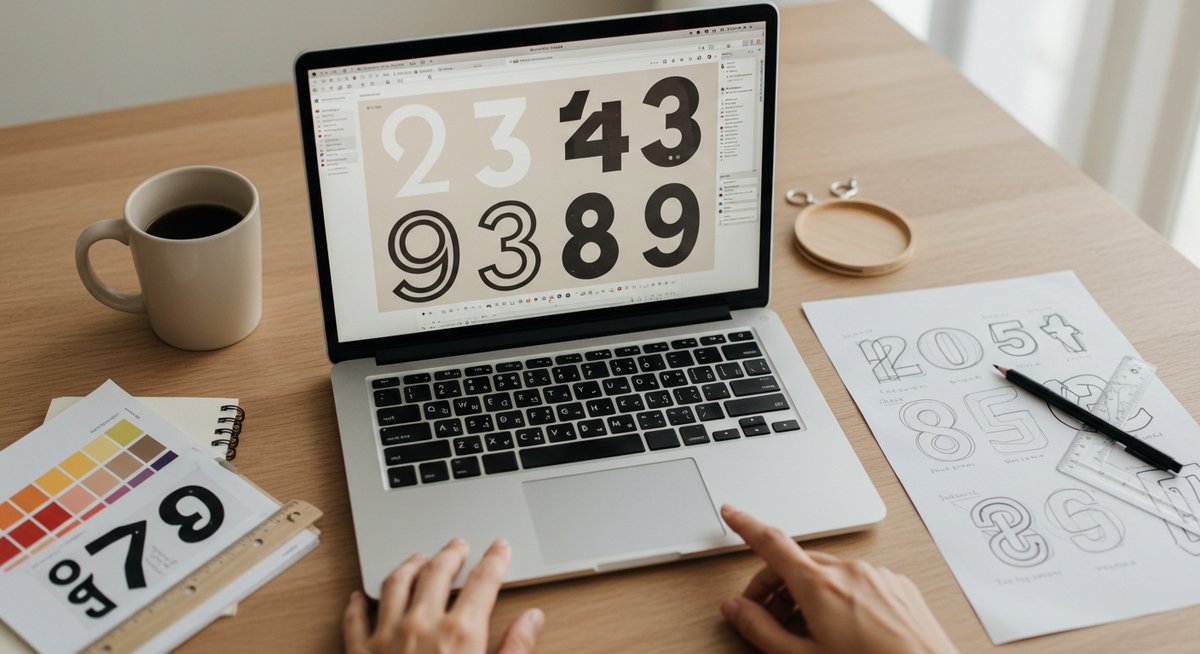
デザインで数字の見え方が変わると、伝わり方がぐっと良くなります。ここではCanvaで使う数字フォントに絞って、おすすめフォントや選び方、使い方のコツをわかりやすくまとめました。読みながら自分のプロジェクトに合うフォントが見つかるように書いていますので、気軽に試してみてください。
Canvaで使う数字のフォントのおすすめはこれ
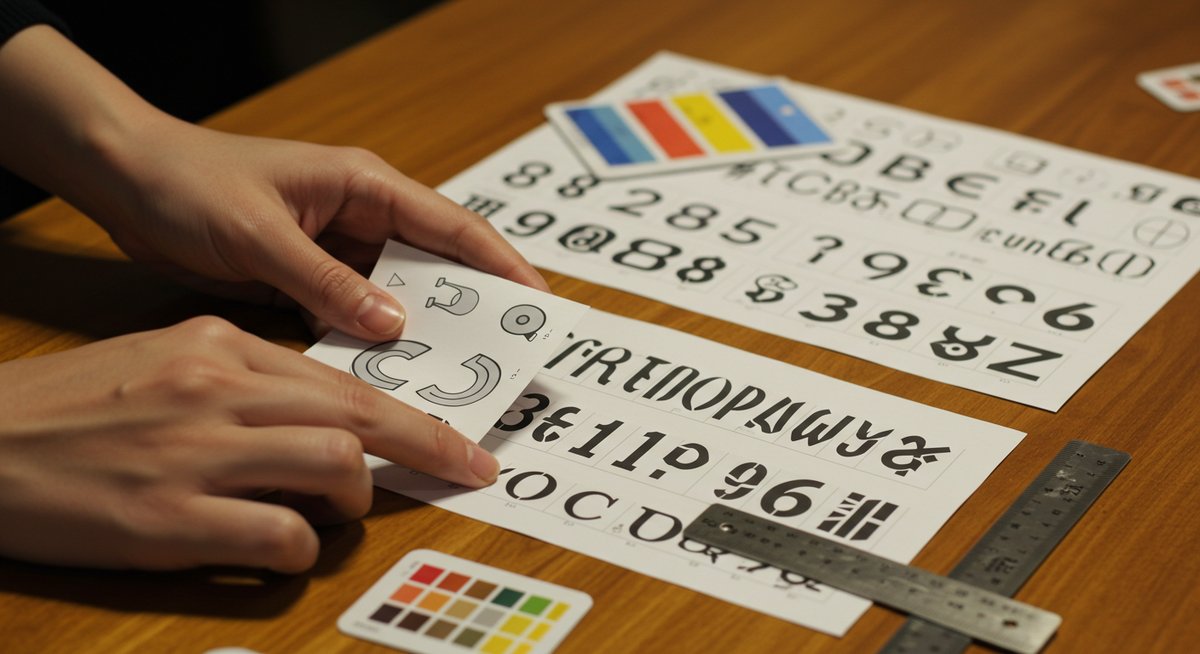
ここではタイトルや見出し、グラフ、金額表示、手書き風まで用途別に向くフォントを紹介します。各フォントの特徴と、どんな場面で使うと効果的かをシンプルにまとめました。実際にCanvaで試すときの参考にしてください。
見出し向けのおしゃれな欧文フォント Lovelace Road Race
Lovelace Road Raceは華やかで個性のある欧文フォントです。数字のラインが細く伸びる部分と太い部分のコントラストがあり、見出しやバナーで目を引く効果があります。特にイベント告知やファッション系のデザインで映えます。
数字は装飾性が高いため、大きめサイズで使うのが向いています。小さく表示すると細部がつぶれやすいので注意してください。スペースに余裕がある見出しや、ビジュアル重視のサムネイルに合わせるとバランスが良くなります。
使う際は文字間を少し詰めたり、影をつけて立体感を出すとさらにおしゃれに見えます。背景はシンプルな単色や淡いグラデーションにすることで数字が浮き立ちます。
グラフや表で読みやすいゴシック系 DIN Next Noto Sans
DIN NextやNoto Sansは直線的で安定感のあるゴシック系フォントです。数字の輪郭がはっきりしているため、グラフや表、インフォグラフィックでの読みやすさに優れます。視認性を重視する場面で安心して使えます。
桁が多くなる数値や小さなフォントサイズでも判読しやすく、資料やレポート、プレゼン資料との相性が良いです。等幅に近いプロポーションのフォントを選ぶと、表組みで桁が揃いやすく見栄えが整います。
配色はコントラストを意識するとさらに読みやすくなります。背景が濃い色なら白や淡い色の数字を、淡い背景ならダークな色を使うと視認性が上がります。
金額や日付表示に向く安定したフォント Oswald Futura
OswaldやFuturaは角が整っていて、金額や日付の表示に向く落ち着いたフォントです。視線を奪わずに情報を伝えられるため、ECサイトの価格表示やイベントの日程案内などで使いやすい特徴があります。
桁が連なる場面でも見やすく、太さのバリエーションがあれば強調したい部分だけ太字にすると読みやすくなります。数字のみ太くするなどアクセントをつけると重要な情報を強調できます。
画面や紙面での馴染みも良いので、ブランドの本文フォントに近い系統を選ぶと統一感が出ます。余白を適度に取って読みやすさをキープしましょう。
手書き風で親しみが出るフォント Allura Dancing Script
AlluraやDancing Scriptは手書き感のあるフォントで、カジュアルさや親しみを出したい時に向いています。日付や小さな数値をアクセントとして使うと、堅すぎない印象になります。
ただし装飾が強いので長い数列や重要な数値の表示には向きません。短めの数字や見出しの一部で使うとデザインに温かみが加わります。
文字サイズを大きめにして読みやすさを確保し、背景にはシンプルな色を使うと文字が浮かび上がります。合うフォントと組み合わせて使うことでバランスよく見せられます。
日本語デザインに合わせやすい無料フォント Noto Sans JP 筑紫Aオールド明朝
Noto Sans JPはクセが少なく読みやすい日本語ゴシックで、数字との相性も良いです。筑紫Aオールド明朝はセリフで品のある印象を与えます。和文デザインの中でも数字の雰囲気を変えたい時に便利です。
和文が主体のデザインでは、日本語フォントと欧文数字の混在に注意すると統一感が出ます。Noto Sans JPは無料で使える点も嬉しいポイントです。
用途に応じてゴシックと明朝を使い分けると、情報の階層が伝わりやすくなります。数字もフォントによって表情が変わるので、デザイン全体のトーンと合わせて選んでください。
数字フォントを選ぶときに見るべきポイント
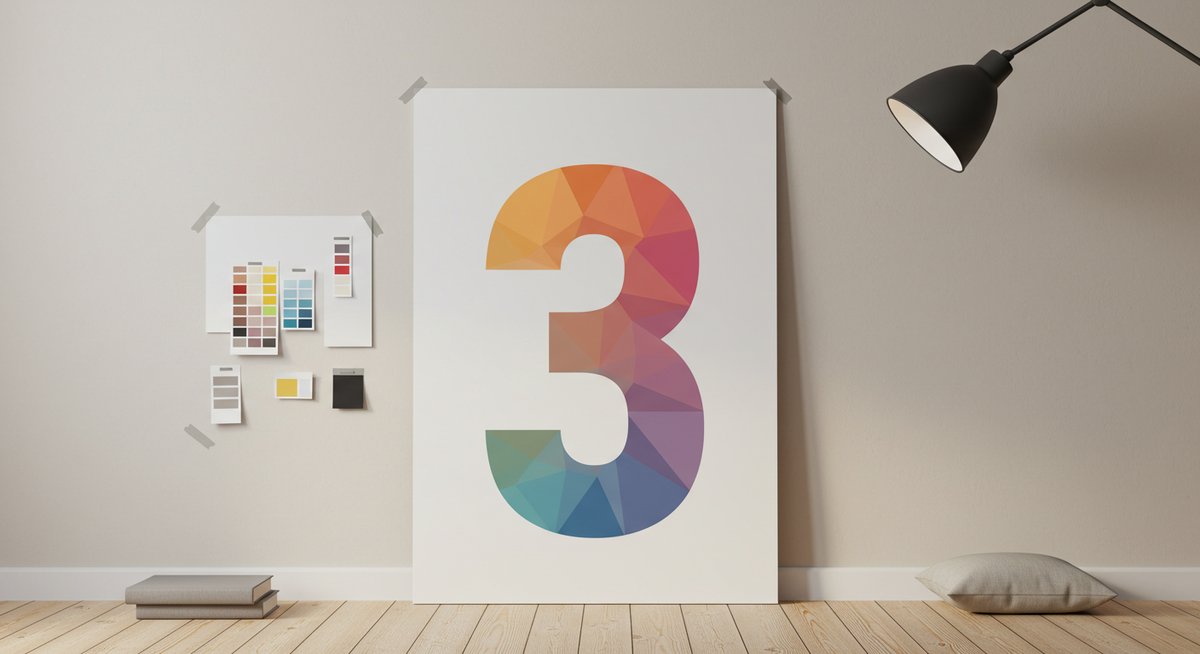
フォント選びではいくつか押さえておくとよいポイントがあります。読みやすさ、用途、表示サイズ、ライセンスなど、実際の制作で困らないためのチェック項目をまとめます。これらを確認しながら選ぶと失敗が少なくなります。
数字の形やプロポーションを比べる方法
数字の形はフォントごとにかなり違います。横幅や高さ、丸みの有無で印象が変わるため、同じサイズで並べて比べるのがおすすめです。見出し用か本文用かで適したプロポーションが違います。
比較の手順は簡単です。使いたい数字列(例:2025/10/07や¥9,800)を同じサイズで並べて表示し、視認性や雰囲気をチェックします。小さくしても読めるか、大きくすると崩れないかも確認しましょう。
デザインに合わせて、数字の丸さや角張り、幅のバランスが合っているかを見て決めるとまとまりやすくなります。複数候補をスクリーンショットして比べるのも手です。
フォントの太さとウェイトで見やすさを判断する
ウェイトの違いで読みやすさが大きく変わります。太めだと遠くからでも読み取りやすく、細めだと上品な印象になります。用途に応じて複数のウェイトがあるフォントを選ぶと応用が利きます。
同じフォントでも太さを変えたときに数字の形が崩れないかを確認してください。細めのウェイトだと小さなサイズで潰れてしまうことがありますし、太すぎると桁間が詰まって見づらくなります。
見出しやバナーでは重め、表や注釈では標準〜細めを使い分けるとメリハリが付きます。実際に出力して確認するのがおすすめです。
桁揃えや文字間の違いをチェックする
桁揃えや文字間(トラッキング)は数値の読みやすさに直結します。等幅フォントは会計や表で桁が揃いやすく、プロポーショナルフォントは見た目のバランスが良くなります。
表組みや価格表示では桁が揃っているとパッと見て比較しやすくなります。文字間を調整できると、桁幅の違いで生じる視覚的なズレを簡単に補正できます。
表示前に少し調整しておくと、最終的なレイアウトが整いやすくなります。各フォントで同じ数列を試してみることをおすすめします。
色と背景で視認性を実際に試す
文字色と背景の組み合わせで見え方が大きく変わります。高いコントラストは読みやすく、コントラストが低いとおしゃれですが判読性が落ちます。使用環境を想定して確認しましょう。
スマホでの見え方はPCと異なるため、両方でチェックすることが大切です。背景が模様や写真の場合は、数字が埋もれないように縁取りや影で補う方法も有効です。
色覚多様性にも配慮するとより親切です。重要な数値は色だけでなく太さや枠で識別できるように工夫してください。
用途別に分けたおすすめ数字フォント集
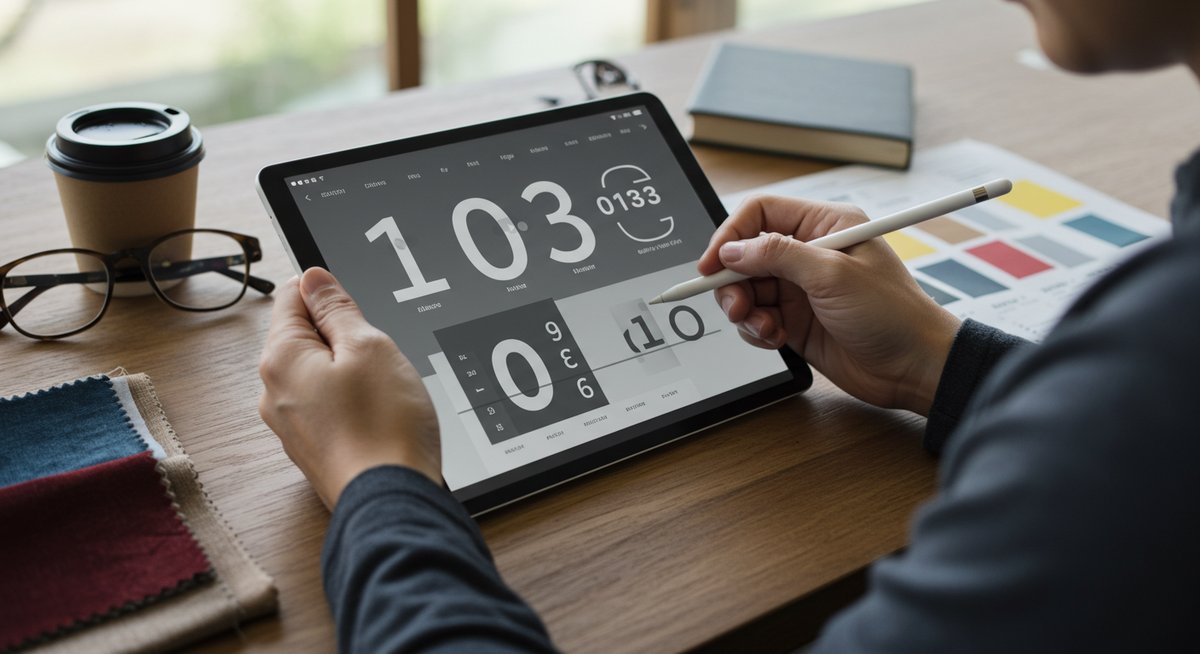
ここでは用途ごとに向くフォントをピックアップしました。どの場面でどんな雰囲気にしたいかを想像しながら選んでみてください。短い説明と活用例を添えています。
見出しやバナー向け欧文フォント Lovelace Road Race
Lovelace Road Raceは視認性が高く華やかな印象を与えるため、見出しやバナーにぴったりです。数字が装飾的でインパクトがあるので、イベント名やセール告知の頭に使うと効果的です。
大きく表示することでディテールが活きます。カラフルな背景や写真の上でも映えるので、ビジュアル重視のデザインに合わせやすいです。読みやすさを保つためにフォントサイズはやや大きめに設定しましょう。
ポスターや広告で使いたい装飾系フォント Copperplate Road Race
Copperplate Road Raceのような装飾系フォントは、ポスターや広告でアクセントに使うと印象に残ります。太さや装飾があるため遠目でも目立ちますが、長い数列には向きません。
見出しの一部や強調したい価格帯などに使うと効果的です。背景はシンプルにして文字が負けないように調整してください。
グラフや表で読みやすいゴシック系 DIN Next Oswald
DIN NextやOswaldはグラフや表に最適です。輪郭がはっきりしており、細かい数値でも読みやすく、データを正確に伝えたい場面で安心して使えます。
等幅寄りのフォントを選ぶと桁が揃いやすく、比較しやすい表になります。色分けや太さを使い分けることで視認性がさらに向上します。
高級感を出すセリフ系 Cardo EB Garamond
CardoやEB Garamondのようなセリフ系は、上品で落ち着いた印象を演出します。高級感を出したいメニューや招待状、ブランド紹介の数値表示に向いています。
細部のディテールが上品さを醸し出すので、フォントサイズや行間を調整して読みやすさを保つことが重要です。
カジュアルな手書き風 Allura Dancing Script
AlluraやDancing Scriptはカジュアルで親しみのある雰囲気を作るのに適しています。短い数字や日付をさりげなく装飾的に見せたいときに使いやすいです。
背景や周囲のフォントとの相性を考え、長い数列は避けると全体のバランスが保てます。
日本語デザインに合うフォント Noto Sans JP 筑紫明朝
Noto Sans JPは汎用性が高く、和文デザインの中で自然に溶け込みます。筑紫明朝は和の雰囲気を出したいときに合います。数字は和文テキストとの調和を意識して選んでください。
和文主体のデザインでは、日本語フォントと欧文数字の見た目を合わせると統一感が出ます。無料で使えるものも多いので、まずは試してみるとよいでしょう。
Canvaで数字フォントを使うときの操作と工夫
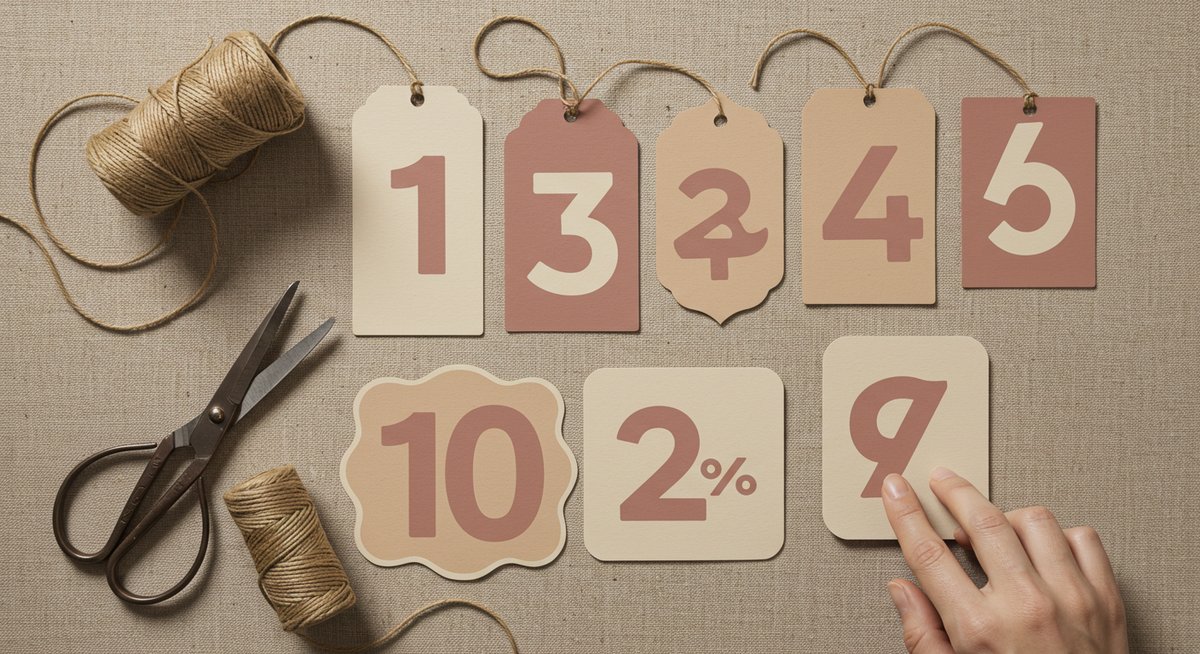
最後に、Canva上での使い方やちょっとしたコツを紹介します。フォントを追加したり、数字だけ目立たせたり、出力時の注意点まで実務で便利なポイントをまとめます。
フォント追加の手順と注意点
Canvaでフォントを追加する場合は、アップロード機能を使います。フォントファイルは対応形式(通常はOTFやTTF)を用意してアップロードしてください。アップロード後はプロジェクト内で選んで使えます。
注意点としては、ライセンスの確認を必ず行うことです。フォントによっては商用利用が制限されている場合があります。また、同じフォントでもウェイトが別ファイルの場合があるので、必要なウェイトを揃えておくと後で便利です。
グラデーションを文字に使うと豪華に見えますが、小さいサイズでは視認性が落ちることがあるため、主要な数字には単色のはっきりした色を使うのがおすすめです。
出力時のフォント崩れを防ぐチェック項目
出力前には必ずプレビューで文字の崩れを確認してください。特に外部アップロードしたフォントは埋め込みがうまくいかない場合がありますので、PDF出力や画像出力で意図した通りになっているかを確かめましょう。
予備として、画像化してから配置する方法や、必要ならアウトライン化(ベクター化)できる環境で処理するのも一案です。スマホ表示と印刷で差が出ることもあるので、目的に合わせた最終チェックを行ってください。
今日から使える数字フォントの選び方
最後に、何を優先するかを一言でまとめると「読みやすさ」と「デザインの目的」のバランスを考えることが大切です。読み手が情報をすぐに理解できるかを基準に選ぶと失敗が少なくなります。
用途に合わせて複数フォントを用意し、見出し・本文・注釈で使い分けると見栄えが整います。まずは少し試してみて、画面や印刷での見え方を確認してみてください。そうすれば、自分のデザインに合った数字フォントが自然と見つかります。